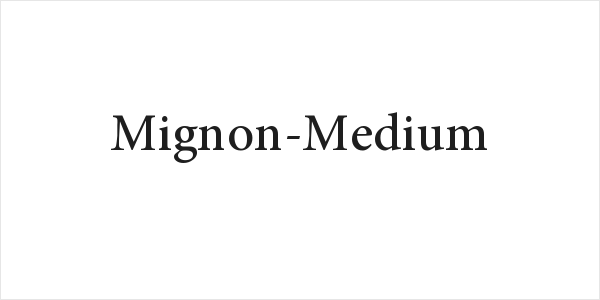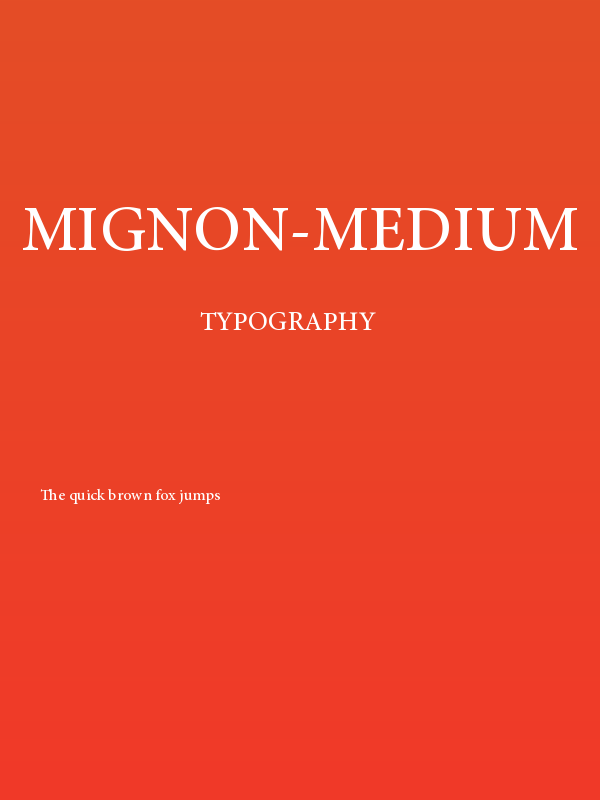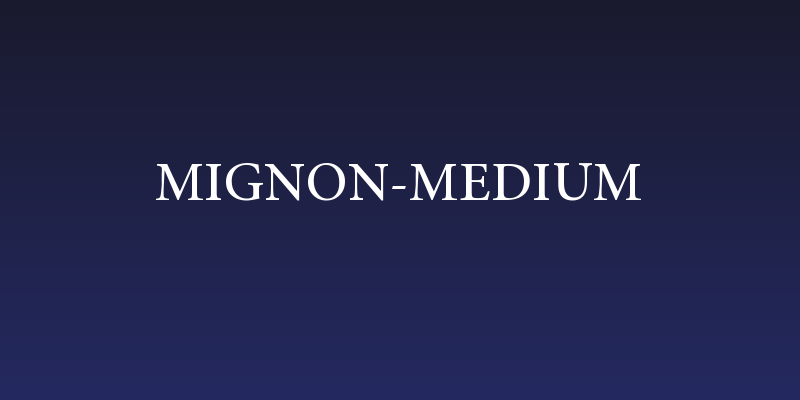
Mignon-Medium Font
✎ Serif
| 分类 | Serif |
| 整体风格 | Classic |
| 使用场景 | Headlines, Body text, Logos |
| 推荐项目 | Ideal for editorial design, book covers, formal invitations, and branding projects that require a touch of elegance and tradition. |